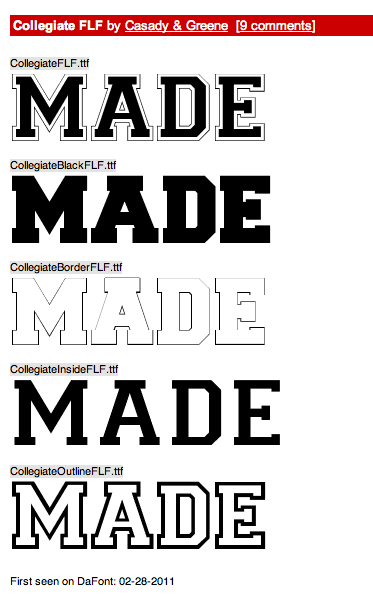
Suche dringend diese Schrift.
Hallo liebe Foren-Mitglieder,
ich soll (muß) für meine Tochter was "zaubern", und dafür benötige ich genau diese Schrift.
Man beachte das beim "M" die Mitte (Spitze) nicht bis nach unten geht und über dem "A" ein Querbalken
sitzt. Ich habe nun mittlerweile gefüllte 10 Tage gesucht, aber nichts gefunden, das Problem ist das "M".
Danke, aber diese Schrift hatte ich schon versucht. Leider ist auch beim "verzehren" per Photoshop es nicht möglich
die "Spitze" beim M höher zu bekommen.
Du darfst nicht den kompletten Buchstaben verzerren, sondern eben nur die richtigen Ankerpunkte nach oben verschieben. Das geht schon.
Was man auf dem Shirt sieht ist ja auch ein Logo, keine genau so verfügbare Schrift.
ich glaub das ist ne super Idee, da muss ich mich glatt noch einmal ransetzen.
jaaa, das sieht schon mal sehr gut aus, ich glaub das ist ne Basis für Photoshop.
die Vektorbearbeitung solltest Du lieber in Illustrator (oder einem anderen vektorbasierte Programm) vornehmen, das ist für solche Bearbeitungen prädestiniert.  :-)
höre auf Karthrin und nehme ein Vektorzeichenprogramm des geringsten Misstrauens, zB das freie Inkscape. Erzeuge den Text, konvertiere ihn in einen ganz normalen Pfad und greife Dir die Punkte mit dem Anfasser. Im Original wurden vielleicht einfach nur gefälschte Kapitälchen (Small Caps) benutzt oder das M manuell hochskaliert. Zwei passende Schriften zum verdengeln hast Du hier ja schon genannt bekommen.
... so nebenbei, auch ich finde Powerpoint nicht gerade das gelbe vom Ei und bevorzuge dann doch lieber Keynote.
Danke, aber diese Schrift hatte ich schon versucht. Leider ist auch beim "verzehren" per Photoshop es nicht möglich
die "Spitze" beim M höher zu bekommen.
hehe, ich musste lachen, sorry. »verzehren« per photoshop! :hammer:
natürlich sind vektorprogramme besser geignet, allerdings wenn einem nur photoshop zur verfügung steht sollte es ein kinderspiel sein.
die textebene in eine form umwandeln und dann ist es kein thema.
Ich dachte eher, Uwe spielt auf böses kommerzielles Programm vs. OpenSource-Software rettet die Welt an …
Neeee! Schnitzel hat es richtig erfasst. GIMP ist da etwas harmloser, das liegt aber auch bei der Zielgruppe. Das Potential hätte GIMP aber trotzdem. Wenn man es genauer betrachtet ist bei OSS die Hemmschwelle sogar geringer und damit die potentielle Schadwirkung sogar höher.
:tutor:
Ein sehr großes Problem ist auch unabhängig von der verwendeten Software und ob diese kommerziell oder frei ist. So werden verschiedene Elemente einfach zusammengeworfen ohne Rücksicht auf die Konsistenz der Gestaltung. Da kann man mit nur zwei Elementen, also zB eine fotorealistische, strukturierte Wand als Hintergrund und einem grafischen Logo, bereits vollkommen die Gestaltung versauen. Ok, als bekennender Minimalist hätte ich die unnötige Wand rausgeworfen und dann wäre alles wieder konsistent. Legt man ein Logo vor eine Struktur, so muss dieses mit Bumpmaps und Co auch auf den Hintergrund richtig aufgesetzt werden. Oder aber als virtuelles Schild aufgeschraubt ... Das Logo sollte passend zu fotorealitischen Hintergründen auch fotorealistisch aufgearbeitet werden. Oder aber man macht eine unfotorealistischem rein grafische Gestaltung. Das bevorzuge ich idR, denn das spart Zeit und Aufwand.
Das halte ich für eine gewagte These. Photoshop ist einfach der Inbegriff für Bildbearbeitungsprogramm – so wie Word der Inbegriff für Textvearbeitungsprogramm ist. Aber es denkt ja auch keiner, er wäre Autor, nur weil er wie andere professionelle Autoren auch Word benutzt.